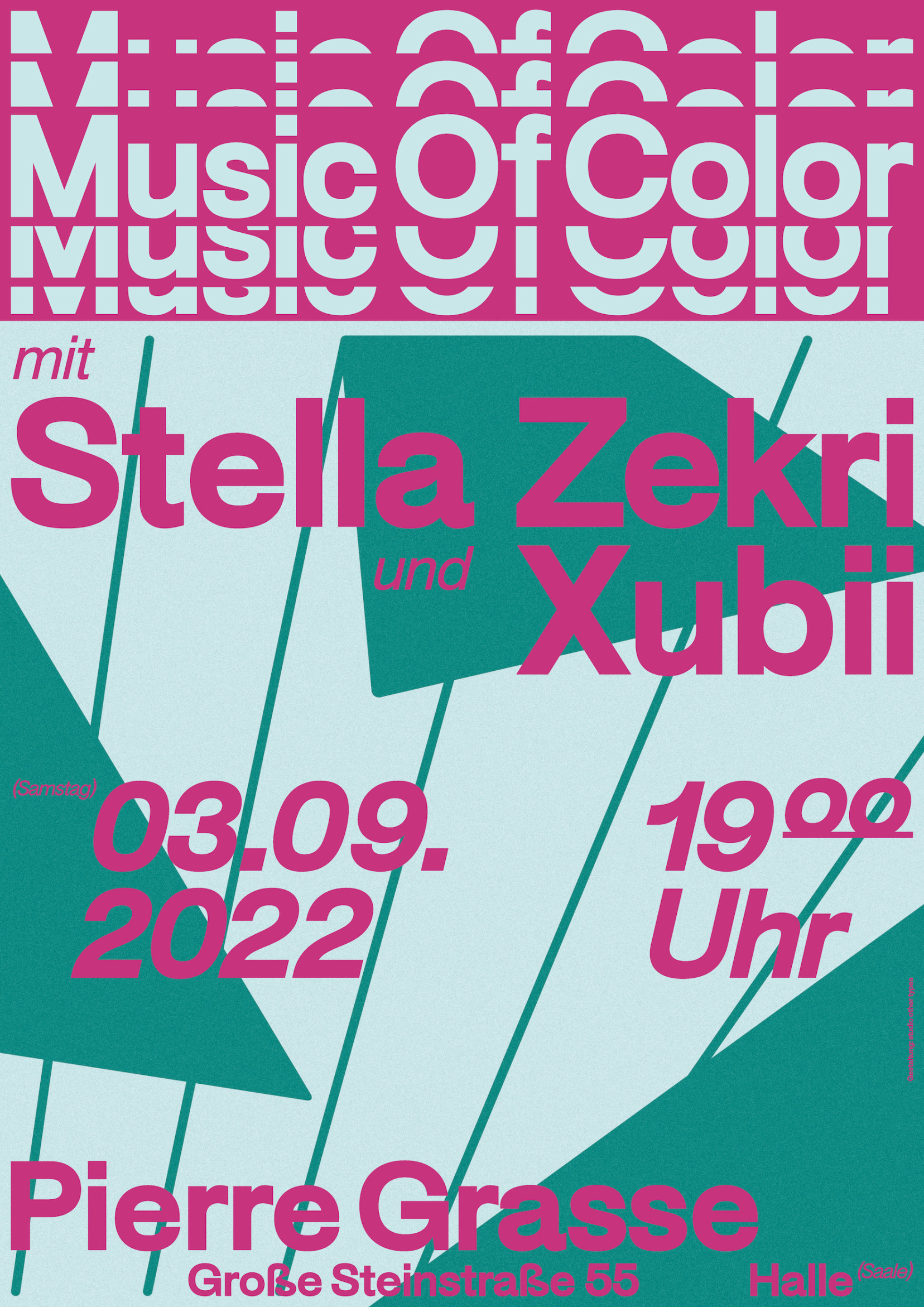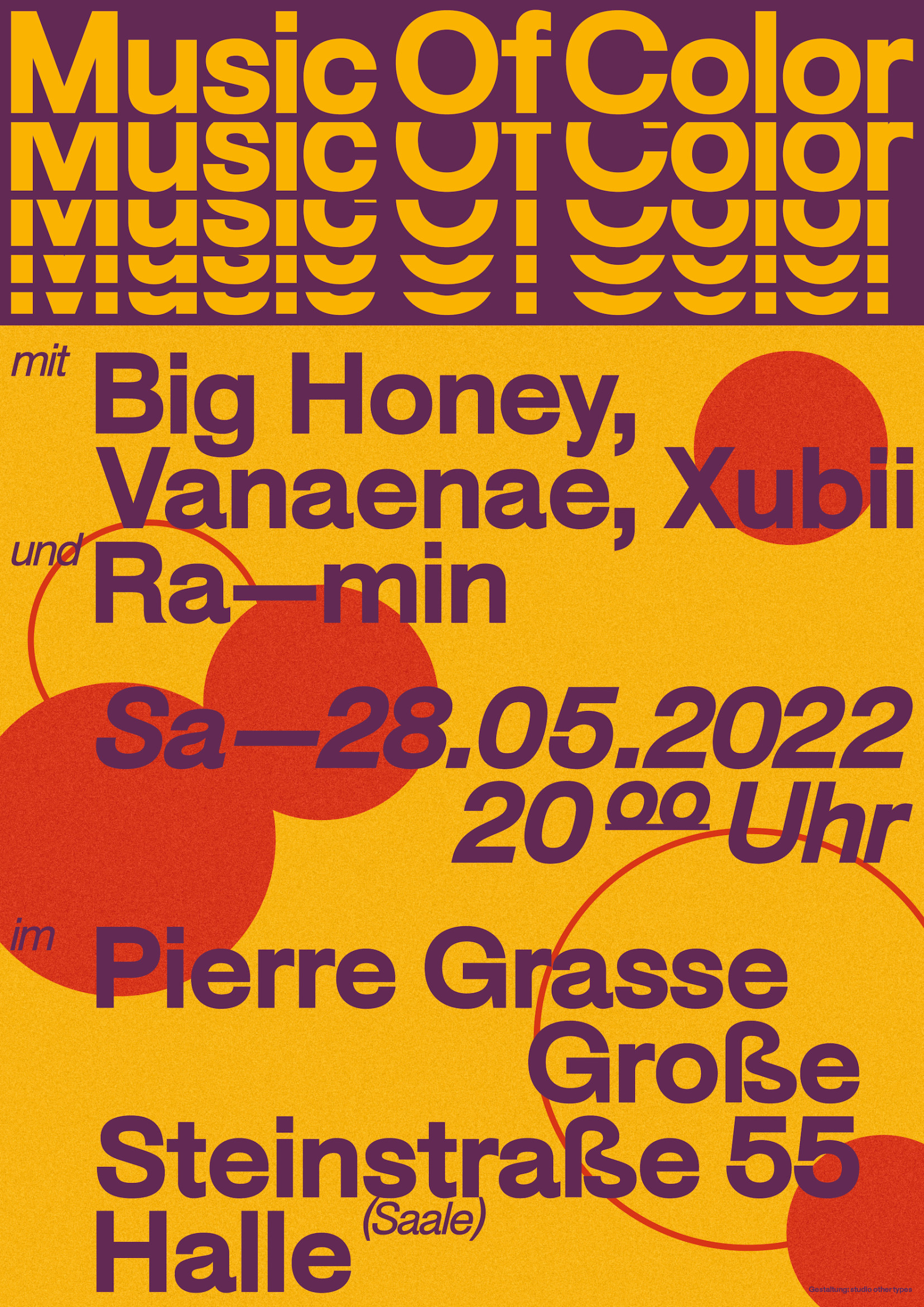
Music Of Color @ Pierre Grasse
Plakatserie für eine fortlaufende Tanzveranstaltung des Kollektivs Music Of Color in Halle an der Saale. Formen und Farben strahlen eine klangvolle Atmosphäre aus und illustrieren die Offenheit und Vielfalt der gespielten Musik und der Menschen, die zusammenkommen.
Schrift: Default Sans von Scott Vander Zee